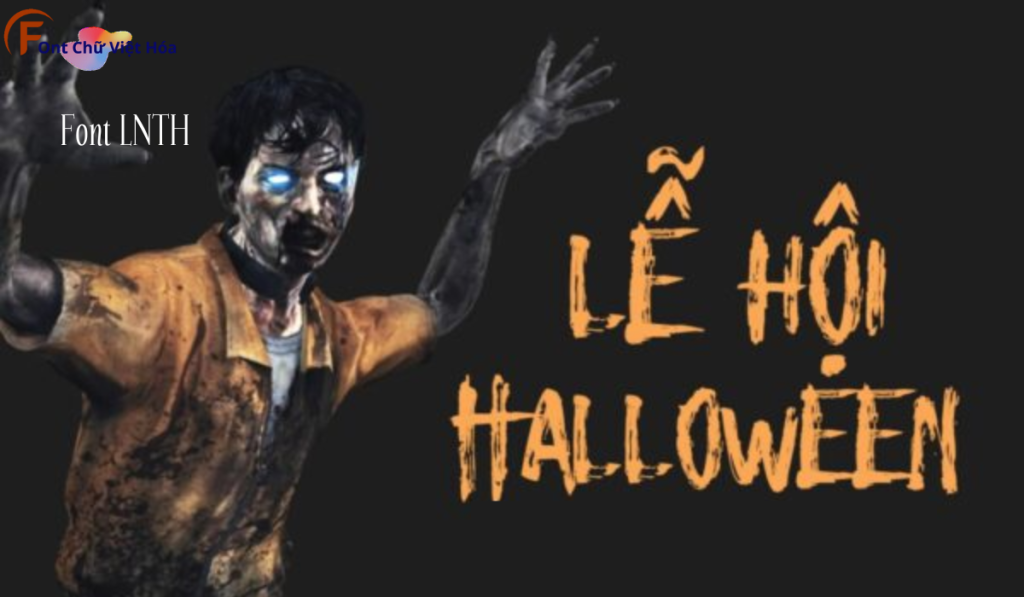
Font LNTH Zombies Việt Hóa
Font LNTH Zombies Việt Hóa là một font chữ độc đáo, thuộc bộ LNTH, với thiết kế lạ mắt và ấn tượng. Phong cách của font này phù hợp với các dự án thiết kế cần sự độc đáo và thu hút, như poster phim, bìa sách, hoặc thiệp mời. Font LNTH Zombies Việt Hóa mang đến sự độc đáo và dễ nhận diện, ứng dụng trong các lĩnh vực sáng tạo. Đặc điểm hình dạng của font bao gồm các đường nét lạ mắt và phức tạp, giúp tăng tính thẩm mỹ và sự chú ý. Việc Việt hóa font giúp người dùng dễ dàng sử dụng trong các thiết kế tiếng Việt, mang lại sự tiện lợi và linh hoạt.